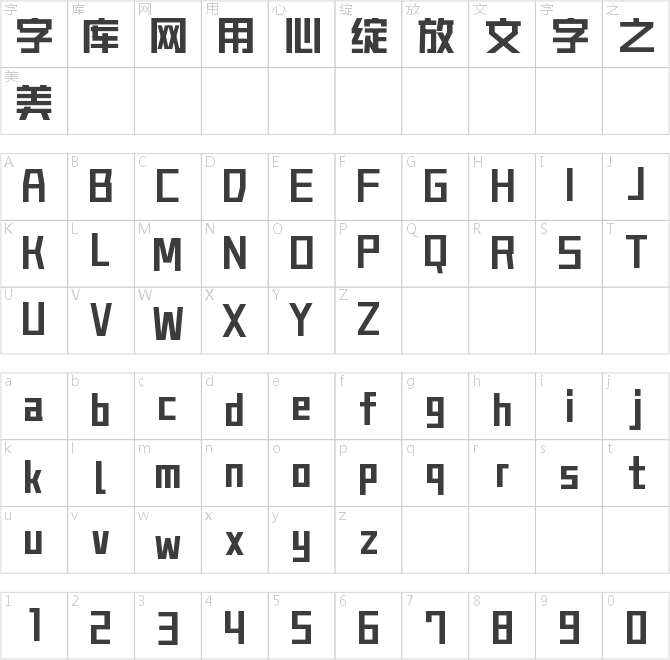
華光鋼鐵直黑_可變體 詳情頁
字體名稱: 華光鋼鐵直黑_
華光鋼鐵直黑_可變體
華光鋼鐵直黑_可變體 是一套可以自由變換粗細的GB2312字體。在PS和AI2018CC以上版本可直接使用。平直的筆畫,規整的線條,扎實的結構,方正的字形,此套字體表現出剛正不阿、一絲不茍的品質。適用于廣告雜志、標題標語、影視包裝網頁設計等場景。